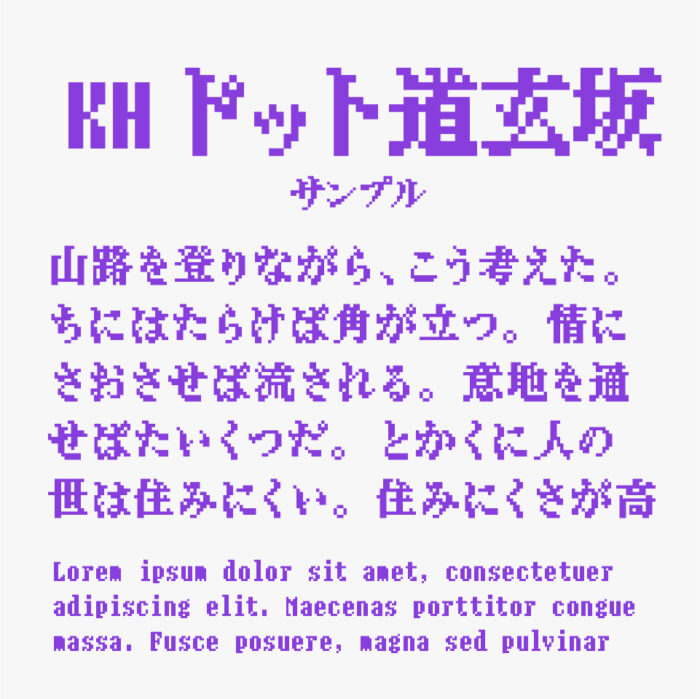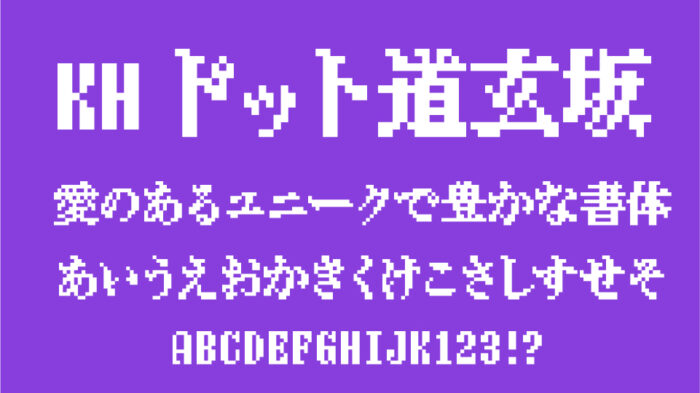
KHドット道玄坂フォントは、書体デザイナーの平木敬太郎氏が1991年から1996年にかけてリリースされたフォントを再構成したドットフォントです。
KHドットフォントは「KHドット秋葉原」「KHドット神楽坂」「KHドット日比谷」など地名を冠としてシリーズ展開されているドットフォントです。
その中でもKHドット道玄坂フォントは、太めな明朝体をベースとして作られているフォントです。太めな明朝体ドットは珍しいタイプのドットフォントとなっています。